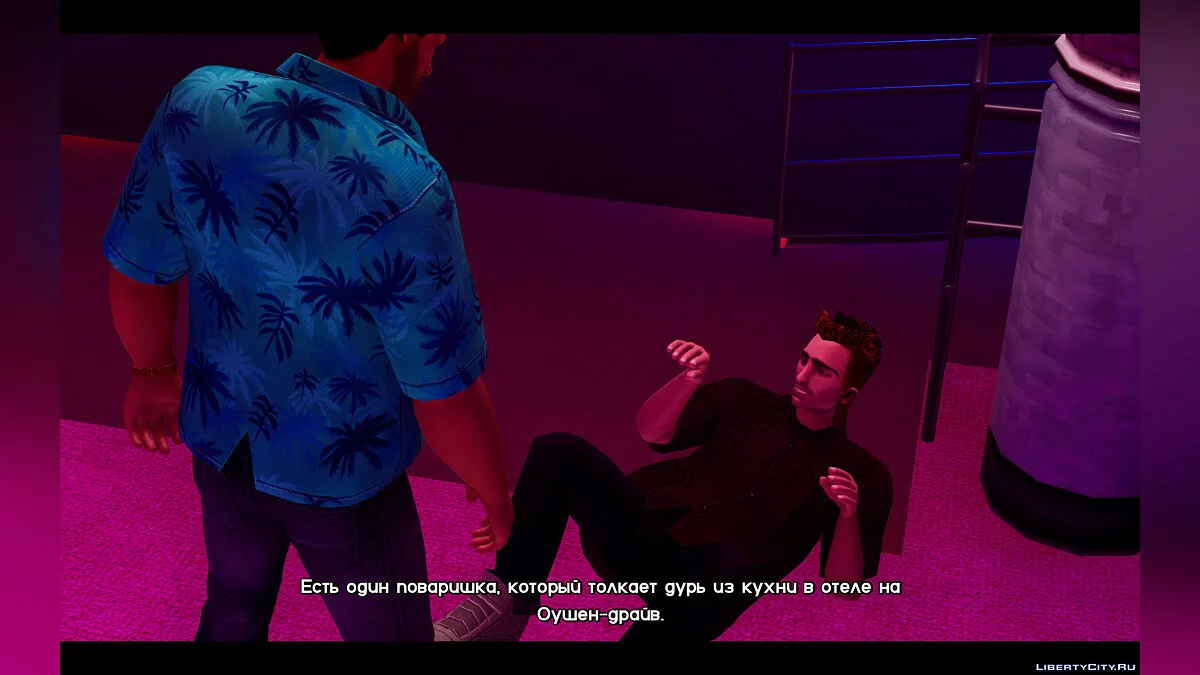
Оригінальний шрифт з підтримкою кирилиці
З самого виходу трилогії мене дратував неправильний шрифт в іграх. Так як нові шрифти — не текстури, а векторні накреслення, мені довелося знайти оригінальний шрифт, з якого відмальовувалася текстура, і вручну намалювати до неї російські літери. Тепер Vice City виглядає так, як треба.
Оригинальный шрифт с поддержкой кириллицы
С самого выхода трилогии меня раздражал неправильный шрифт в играх. Так как новые шрифты — не текстуры, а векторные начертания, мне пришлось найти оригинальный шрифт, с которого отрисовывалась текстура, и вручную нарисовать к ней русские буквы. Теперь Vice City выглядит так, как надо.